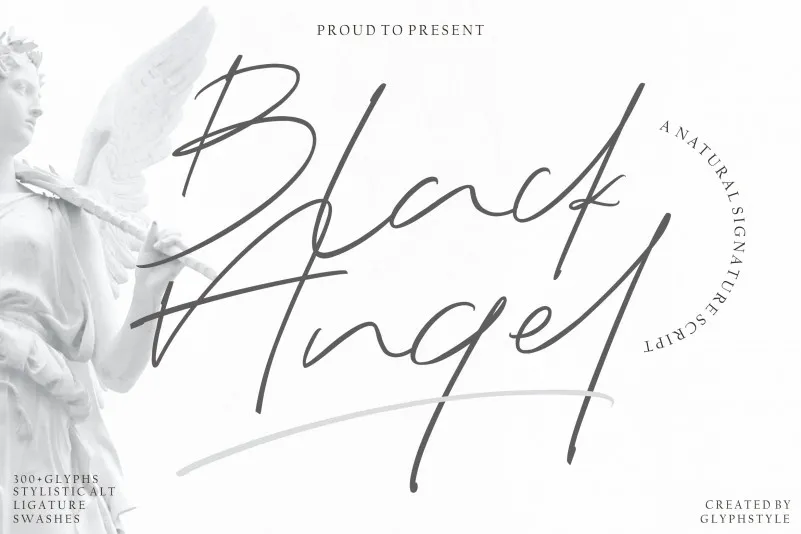
Black Angel – Signature Font – Download Grátis
A Black Angel – Signature Font é uma opção perfeita para designers que buscam manter a elegância e estilo natural de uma assinatura em suas criações digitais. Esta fonte de escrita caiada exala um charme autêntico, oferecendo um texto elegantemente fluido com traços naturais da mão que dão ao design um toque sofisticado e único. Ideal para aplicações como casamentos, identificações, logomarcas, postagens nas redes sociais, anúncios, embalagens de produtos, logos, assinaturas de fotos, convites e material de estaçãoaria, a Black Angel oferece um toque autêntico ao seu trabalho. Suavemente fluida e natural, esta fonte é perfeita para quem deseja incorporar uma atmosfera personalizada em seus projetos, tornando cada projeto um ato de arte singularmente autêntico.